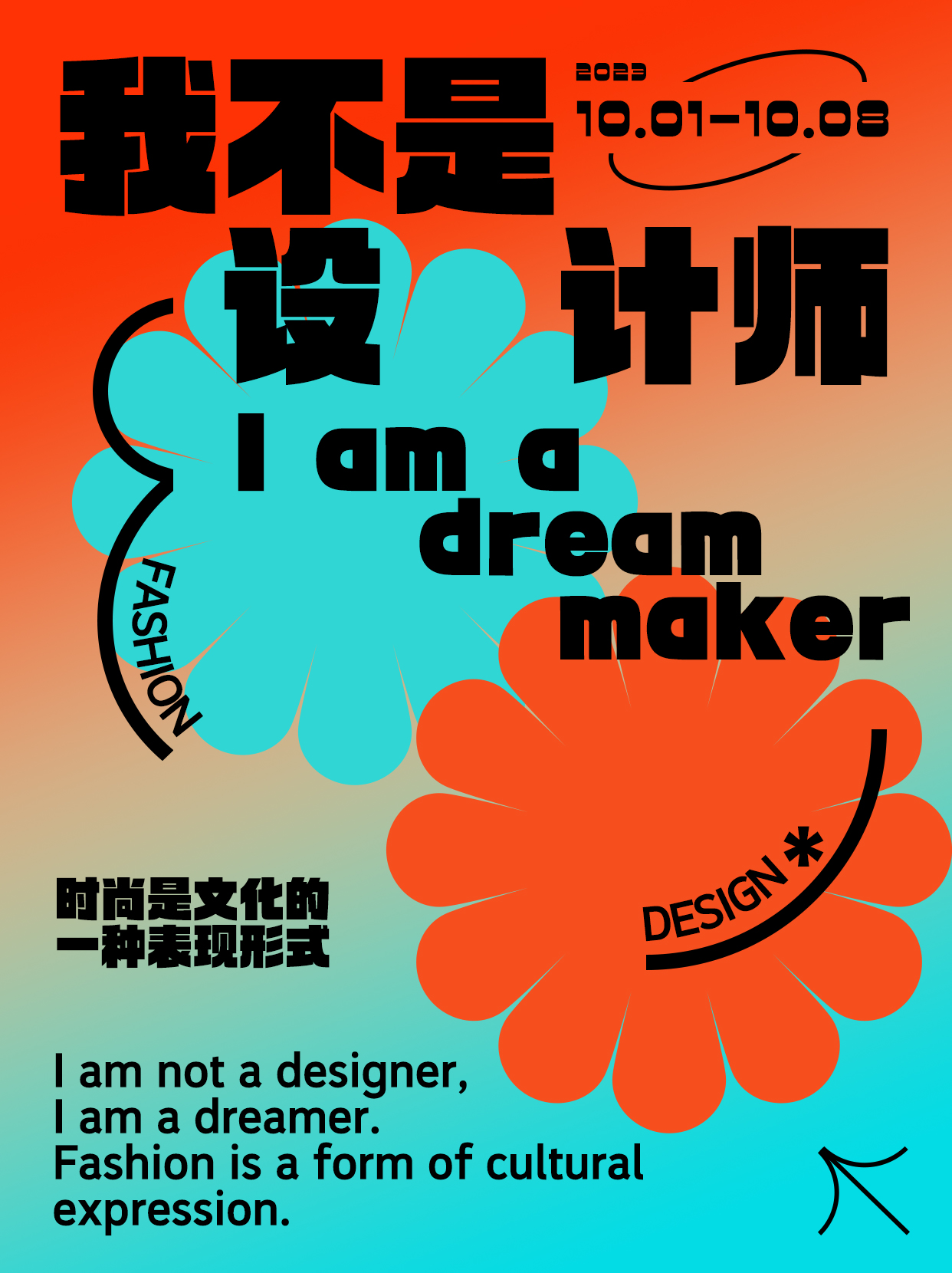
是一款整体方正简洁的黑体,刚柔相济,中宫较大,重心平稳,布白均匀,比例适当,空间结构紧凑,给人一种稳重感。笔画棱角分明、粗壮有力,笔画起收笔为平切,曲线流畅弧度较大,折笔处简约,钩笔画处理灵活,一部分钩笔画微上挑融入曲线元素,一部分钩笔画进行简化去钩,弯钩笔画加入外圆角特点,平衡了整体硬朗的风格。饱满的块面感,视觉效果强烈,版面均匀,更能适应不同的场景需求。